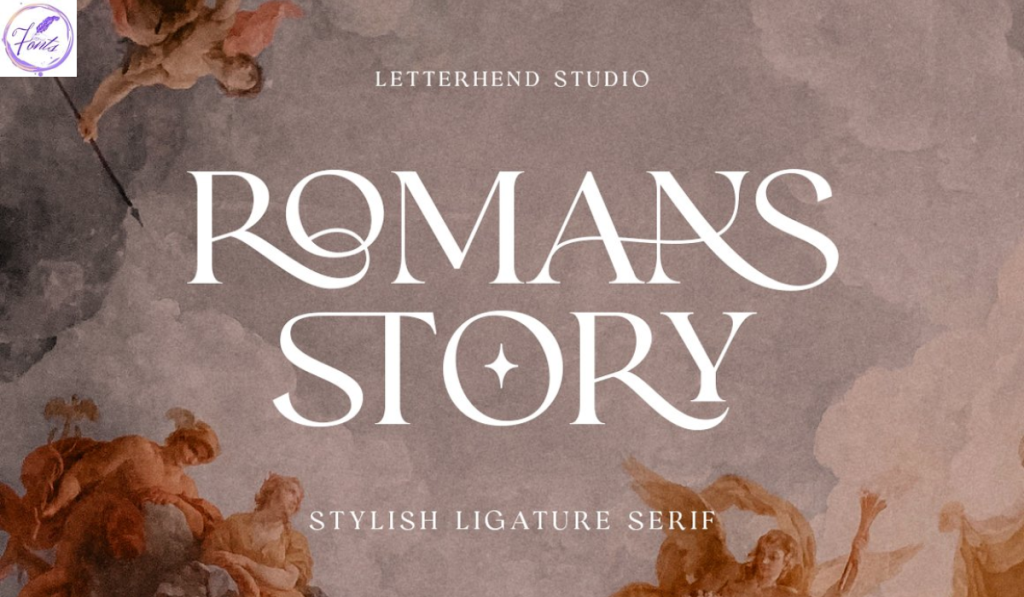
Font Romans Việt hóa
Tác giả: Muflihin Nurhabib
Bộ Font: Romans
Phân loại: Cá tính, độc đáo, thanh lịch
Kiểu chữ: Có chân, serif
Nếu bạn đang tìm kiếm một phông chữ serif cổ điển, sang trọng và đầy cuốn hút cho các dự án thiết kế của mình, font romans chính là lựa chọn tuyệt vời. Được thiết kế bởi nhà thiết kế tài năng Muflihin Nurhabib, romans font mang đến một phong cách quý phái, lịch lãm và đầy tính nghệ thuật. Phông chữ này lấy cảm hứng từ những bản khắc chữ La Mã cổ đại, nhưng được cải tiến để phù hợp với nhu cầu thiết kế hiện đại. Với những đường nét thanh mảnh, duyên dáng và các chi tiết tinh tế, font romans đặc biệt phù hợp cho các dự án liên quan đến thời trang, nghệ thuật, và văn học. Phiên bản Việt hóa của phông chữ này được thực hiện bởi nhóm Fonter.vn, giúp các nhà thiết kế Việt Nam dễ dàng sử dụng font romans trong các sản phẩm của mình.
Đánh giá font romans
Font romans đã nhanh chóng trở thành một trong những phông chữ serif được yêu thích nhất trong giới thiết kế kể từ khi ra mắt vào năm 1989. Theo thống kê từ MyFonts, romans font đã bán được hơn 1 triệu bản quyền, đứng thứ 3 trong danh sách các phông chữ bán chạy nhất mọi thời đại. Nhiều tạp chí và nhà xuất bản danh tiếng như Vogue, Harper’s Bazaar, và Penguin Books cũng đã lựa chọn font romans cho các ấn phẩm của họ.
Năm 1991, romans đã giành giải Certificate of Excellence tại cuộc thi Type Directors Club và giải Best of Category tại Bukvaraz Type Design Competition. Với sự kết hợp hoàn hảo giữa tính thẩm mỹ và tính ứng dụng, font romans xứng đáng là một công cụ đắc lực cho mọi nhà thiết kế muốn mang đến một hơi thở cổ điển, sang trọng cho các sản phẩm của mình.